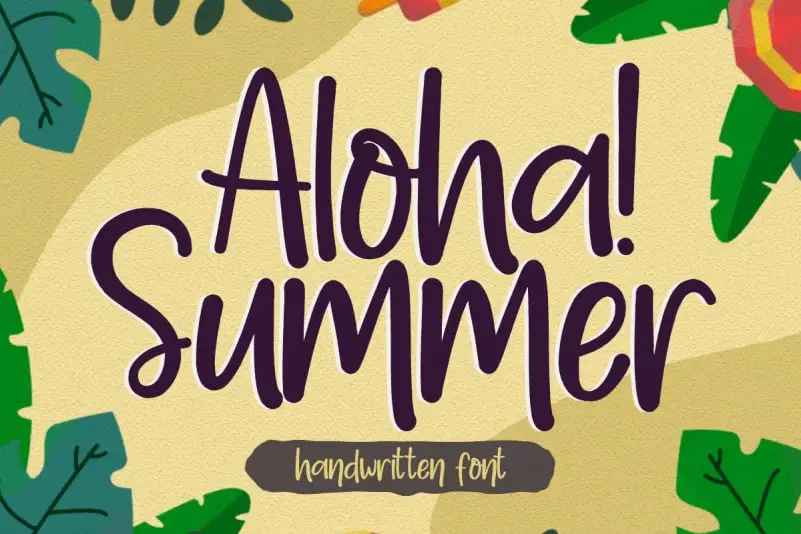
Aloha Summer – Handwritten Font – Fonte Grátis
Aloha Summer - Handwritten Font
Aloha Summer é uma deliciosa e descontraída fonte escrita à mão que se destaca por sua elegância e simplicidade cuidadosamente projetada para torná-la uma verdadeira favorita. Seu arranjo de letras neat e belo o torna um atalho natural e sofisticado para qualquer projeto, seja formal ou não-formal. Perfeito para complementar seu design com uma pegada descontraída que transmite alegria e leveza. Aloha Summer é uma escolha perfeita para aqueles desejando um toque de conforto e amizade em seus trabalhos digitais.